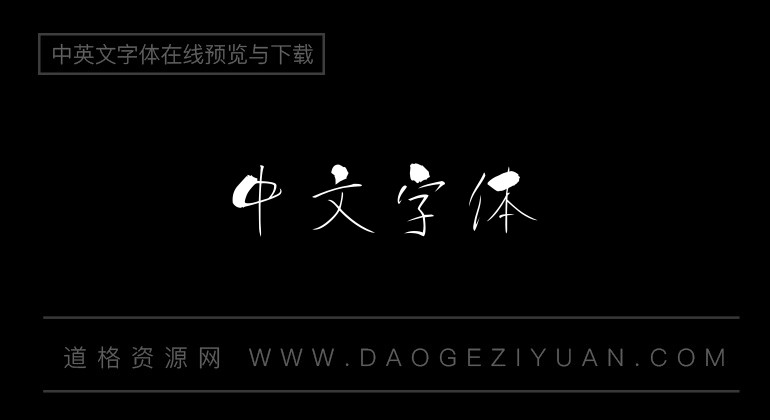
方圆樱花体
方圆樱花体是一款由著名设计师梁群绘制的汉字体,它以樱花为灵感,采用了中国传统的线条绘制手法,融合了新颖的设计元素,形成了独特的风格,具有传统文化的特色。字体结构规整,笔画细腻,线条流畅,曲线优美,字形清晰,视觉效果良好,可以用于各种印刷和设计,是一款具有中国传统文化特色的汉字字体。
方圆樱花体是一款非常不错的手写艺术字体,具有很好的视觉感,适合于文化类的宣传设计、商业类品牌的广告和产品包装设计以及个性化文字排版等较多场景。
方圆樱花体字符映射图